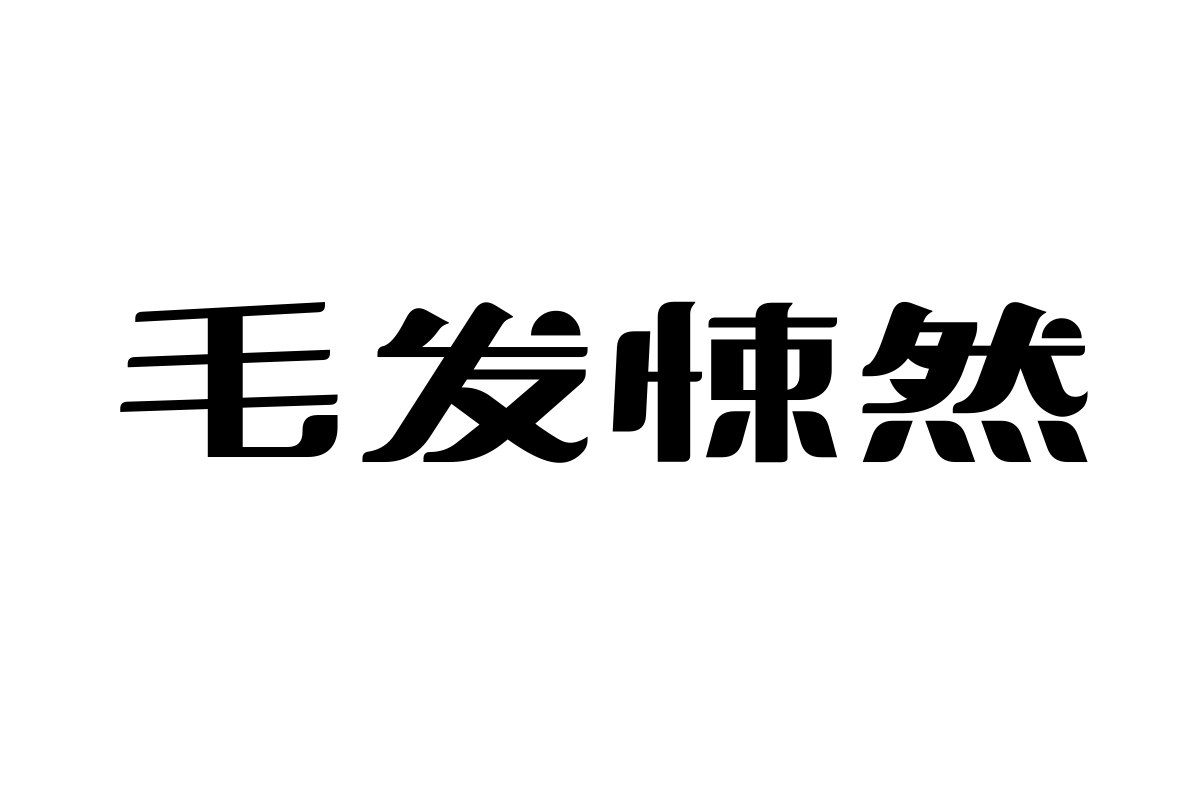
文道雅艺体是一种具有独特美感和艺术价值的字体。它由设计师精心创作,融合了传统书法的韵味与现代审美的理念,形成了一种既典雅又时尚的字体风格。
文道雅艺体的笔画流畅自然,线条柔和而有力,给人一种优雅而高贵的感觉。它的字形结构紧凑而不失灵动,既有严谨的规矩感,又有自由的表现力。在书写过程中,每个字都显得生动而有生命力,仿佛在纸上跳跃着舞动着。
这种字体的特点是简洁而不简单,简约而不失精致。它的每个笔画都经过精心设计,既符合书写规律,又富有个性。无论是楷书、行书还是草书,都能展现出独特的魅力和韵味。
文道雅艺体的应用场景非常广泛,无论是用于正式场合的公文、报告,还是用于个人创作的诗词、散文,都能展现出其独特的艺术魅力。它不仅能够提升文字的艺术价值,还能为阅读者带来愉悦的视觉享受。
总之,文道雅艺体是一种极具艺术价值和实用性的字体,它以其独特的美感和艺术性赢得了广大用户的喜爱和认可。